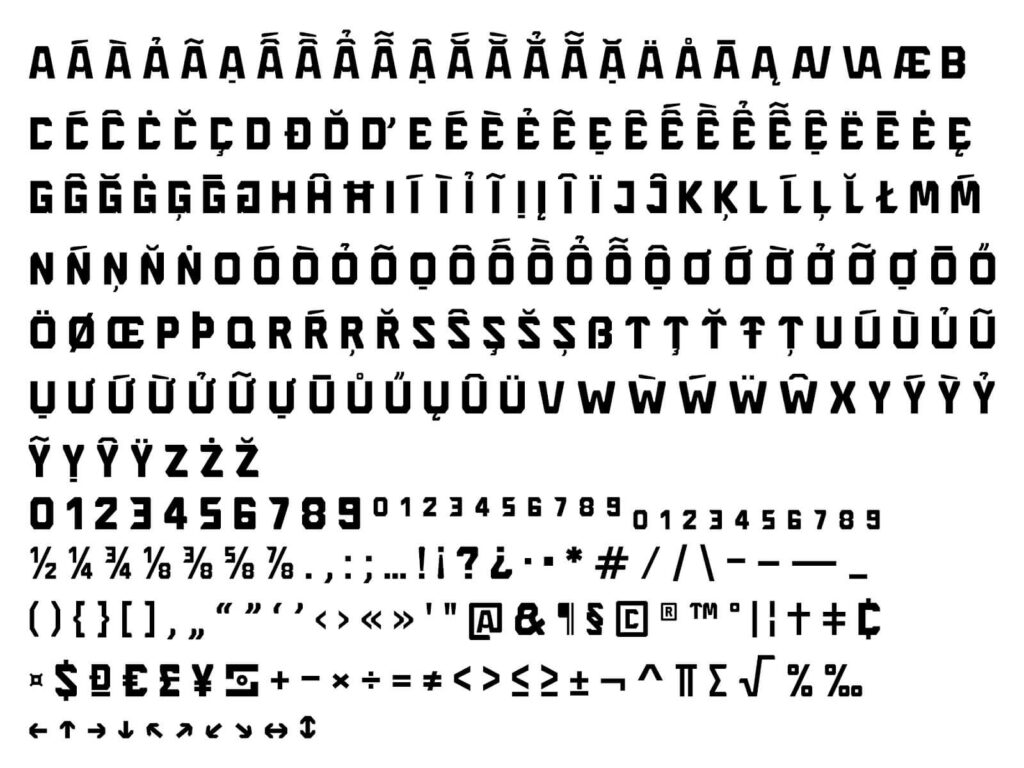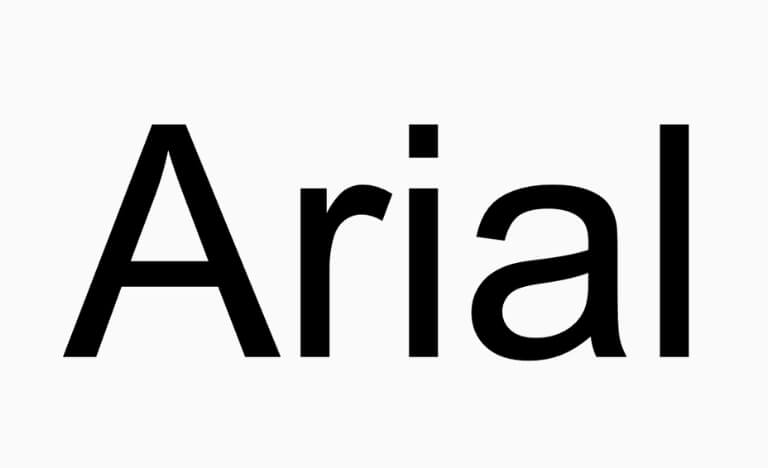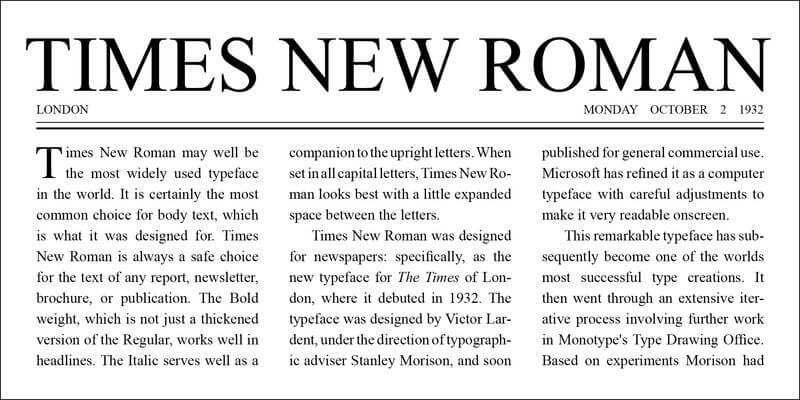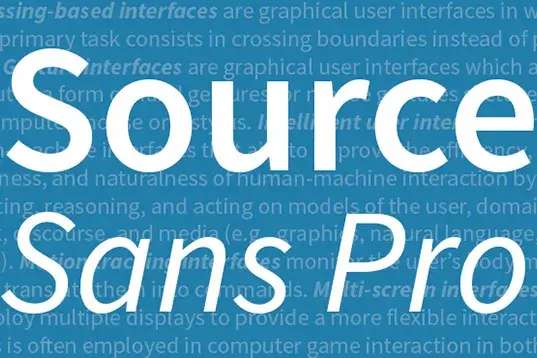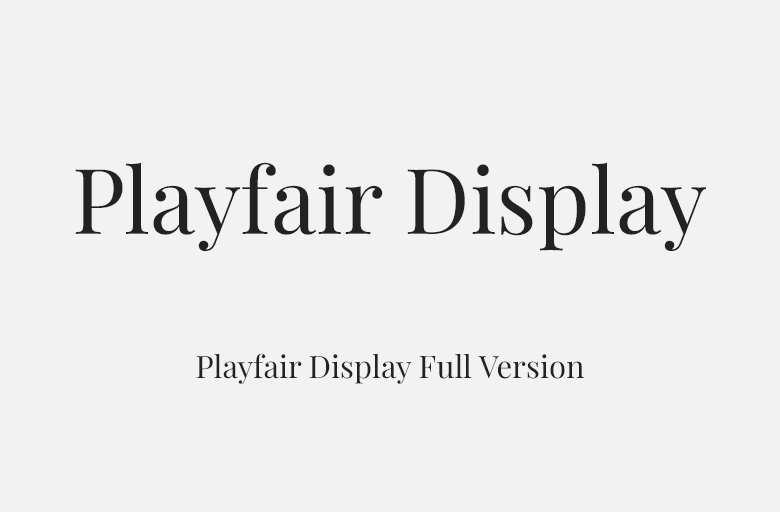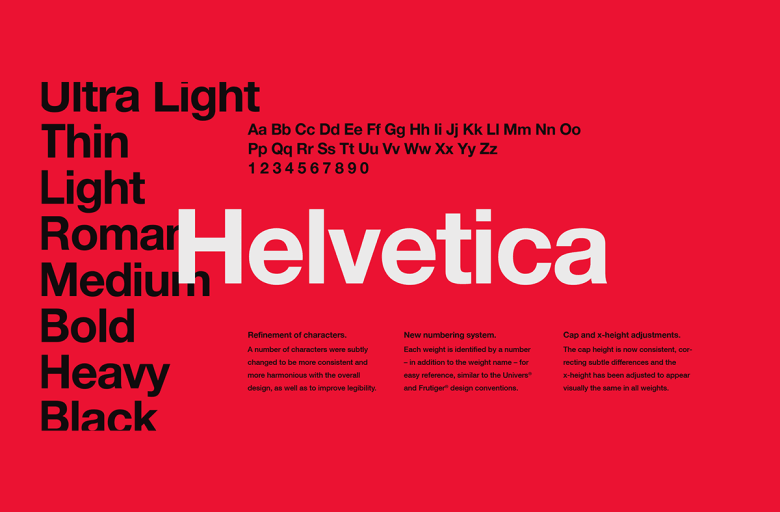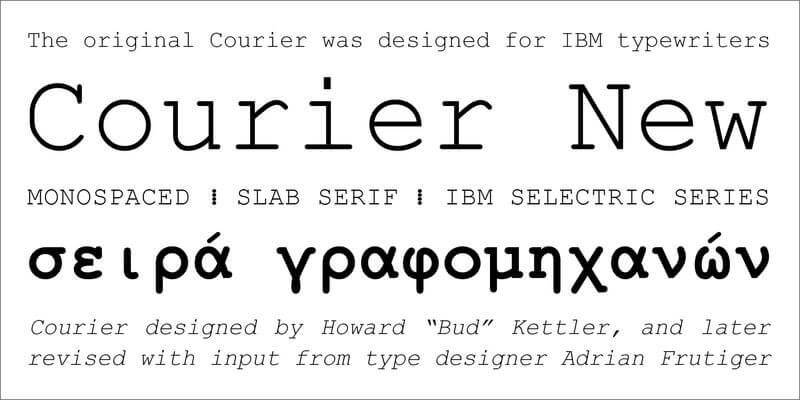
Việc lựa chọn kiểu chữ phù hợp đóng vai trò quan trọng trong việc định hình phong cách và truyền tải thông điệp của website. Để giúp bạn khám phá thế giới typography đa dạng, bài viết này sẽ giới thiệu các nhóm font chữ phổ biến, từ nét cổ điển của Serif đến sự hiện đại của Sans Serif, cùng với những lựa chọn độc đáo khác. Đặc biệt, chúng tôi sẽ mang đến một bộ sưu tập hơn 30 font chữ tiếng Việt miễn phí, được tuyển chọn kỹ lưỡng để nâng tầm thẩm mỹ và trải nghiệm người dùng trên trang web của bạn, mang đến sự chuyên nghiệp và thu hút mà bạn có thể tìm thấy tại hieuseo
Phân loại các kiểu chữ thông dụng trong thiết kế web
Trong lĩnh vực thiết kế web, việc am hiểu sâu sắc về các loại font chữ khác nhau là yếu tố then chốt để xây dựng một hệ thống typography hiệu quả, vừa đảm bảo tính thẩm mỹ, vừa tối ưu trải nghiệm người dùng. Dưới đây là bốn nhóm font chữ chính, mỗi loại mang đặc trưng và ứng dụng riêng biệt:
- Font Sans Serif
- Font Script (Chữ viết tay)
- Font Display
- Font Serif
Kiểu chữ Serif: Nét cổ điển và uy tín
Font Serif là nhóm font chữ đặc trưng bởi sự hiện diện của các đường nét nhỏ, thường được gọi là “chân chữ” hoặc “gạch ngang”, ở cuối mỗi nét chính của ký tự. Đây là một trong những kiểu chữ lâu đời nhất, gắn liền với lịch sử in ấn và các ấn phẩm truyền thống.
Đặc điểm: Có các chi tiết trang trí nhỏ (serif) tại các điểm kết thúc của nét chữ, tạo cảm giác cổ điển và trang trọng.
Công dụng phổ biến:
- Thường được sử dụng rộng rãi trong in ấn, điển hình là sách, báo, tạp chí, nơi cần duy trì sự trang trọng và dễ đọc cho văn bản dài.
- Lý tưởng cho các tài liệu chính thức, học thuật, hoặc các ấn phẩm mang tính truyền thống, lịch sử.
- Góp phần xây dựng cảm giác uy tín, tin cậy và sự ổn định cho các website tin tức, blog chuyên sâu, hoặc các tổ chức có bề dày lịch sử.
Ưu điểm: Mang lại vẻ đẹp cổ điển, trang trọng và có tính thẩm mỹ cao. Các chân chữ giúp mắt dễ dàng theo dõi dòng chữ, đặc biệt hiệu quả với các đoạn văn bản dài trên giấy.
Nhược điểm: Trên màn hình kỹ thuật số, đặc biệt ở kích thước nhỏ hoặc độ phân giải thấp, các chân chữ có thể gây khó đọc hoặc làm mất đi sự rõ ràng của ký tự.
Ví dụ tiêu biểu: Times New Roman, Georgia, Garamond.
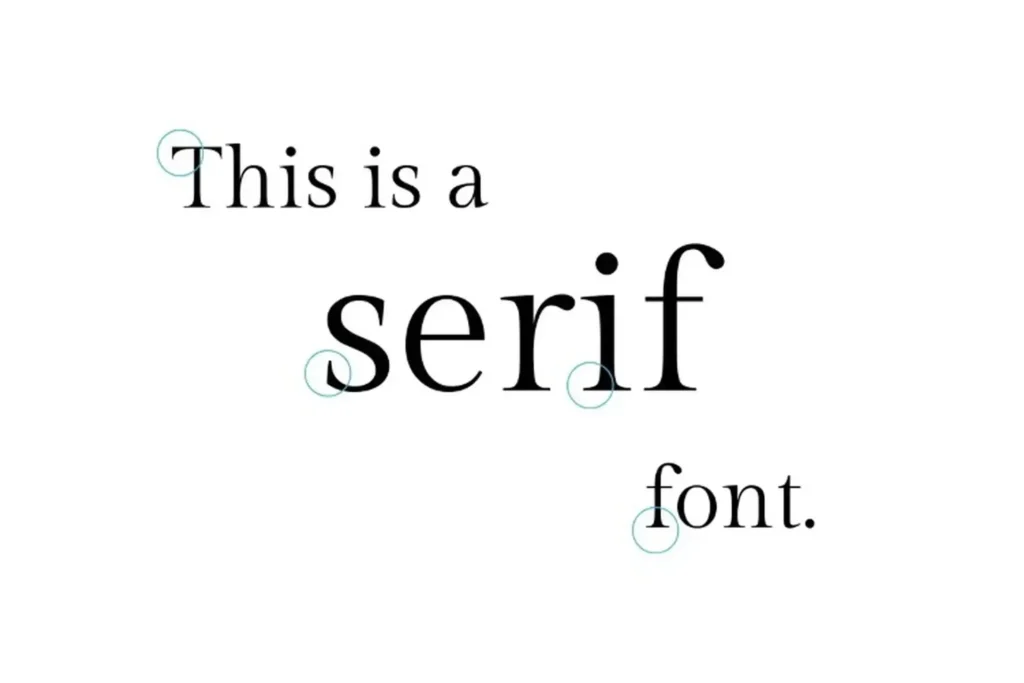
Sans Serif: Sự hiện đại và rõ ràng
Font Sans Serif là nhóm font chữ không có các nét nhỏ (serif) ở cuối các nét chính, mang đến một thiết kế sạch sẽ, hiện đại và tối giản. Sự vắng mặt của chân chữ giúp font Sans Serif trở thành lựa chọn ưu việt trong các thiết kế đương đại và giao diện người dùng kỹ thuật số.
Đặc điểm: Không có các nét nhỏ ở cuối mỗi nét chữ, tạo cảm giác gọn gàng, trực quan và hiện đại.
Công dụng phổ biến:
- Là lựa chọn hàng đầu cho nội dung số, từ màn hình máy tính để bàn đến các thiết bị di động, nhờ khả năng hiển thị rõ nét.
- Thích hợp cho các website có phong cách hiện đại, ứng dụng di động, giao diện người dùng (UI/UX) và các dự án công nghệ.
- Đặc biệt dễ đọc trên màn hình ở nhiều kích thước khác nhau, kể cả khi font chữ được thu nhỏ.
Ưu điểm: Khả năng đọc vượt trội trên màn hình kỹ thuật số, mang lại cảm giác hiện đại, sạch sẽ và linh hoạt.
Nhược điểm: Đôi khi có thể thiếu đi sự cá tính hoặc nét độc đáo nếu không được chọn lựa và kết hợp cẩn thận.
Ví dụ tiêu biểu: Arial, Helvetica, Verdana, Roboto.
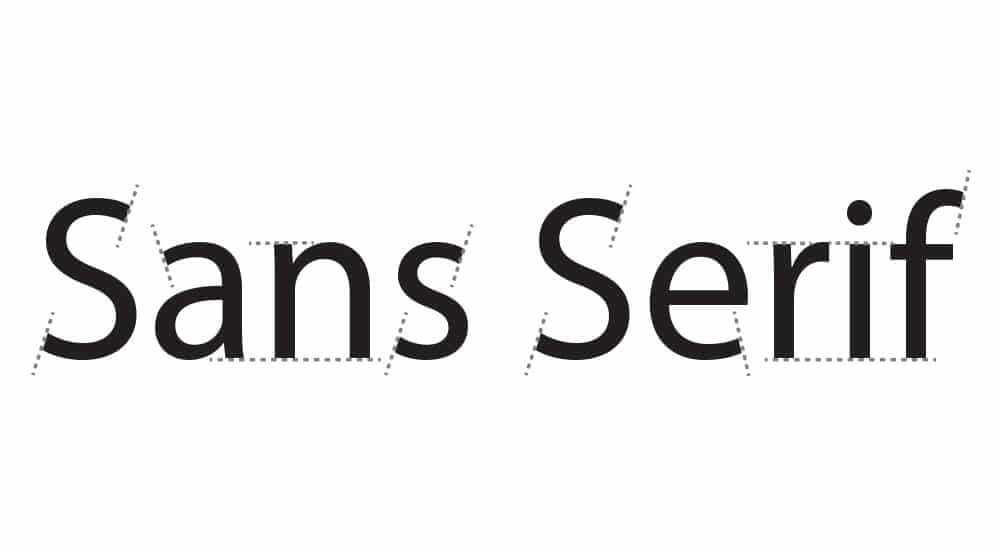
Kiểu chữ viết tay (Script): Sự mềm mại và nghệ thuật
Font Script được thiết kế để mô phỏng chữ viết tay, thư pháp hoặc các kiểu chữ được vẽ bằng tay, mang đến một phong cách cá nhân, mềm mại và giàu tính nghệ thuật. Tùy thuộc vào thiết kế cụ thể, font script có thể tạo nên sự gần gũi, thân thiện, thanh lịch hoặc thậm chí là sang trọng.
Đặc điểm: Mô phỏng chữ viết tay, thường có các nét nối liền mạch, uyển chuyển, hoặc các đường cong mềm mại.
Công dụng phổ biến:
- Thường được dùng trong các thiết kế mang tính cá nhân hóa như thiệp mời, lời chúc, hoặc các ấn phẩm kỷ niệm.
- Tạo điểm nhấn đặc biệt trong thiết kế, thu hút sự chú ý vào một phần nội dung cụ thể.
- Phù hợp cho các website về thời trang, nghệ thuật, ẩm thực, blog cá nhân hoặc các thương hiệu muốn thể hiện sự sáng tạo và độc đáo.
Ưu điểm: Độc đáo, cá tính, mang lại cảm giác ấm áp, lãng mạn hoặc sang trọng.
Nhược điểm: Khả năng đọc thường kém hơn so với Serif và Sans Serif, đặc biệt ở kích thước nhỏ hoặc khi được sử dụng cho các đoạn văn bản dài. Nên dùng hạn chế cho tiêu đề hoặc các yếu tố trang trí.
Ví dụ tiêu biểu: Pacifico, Dancing Script, Brush Script MT.
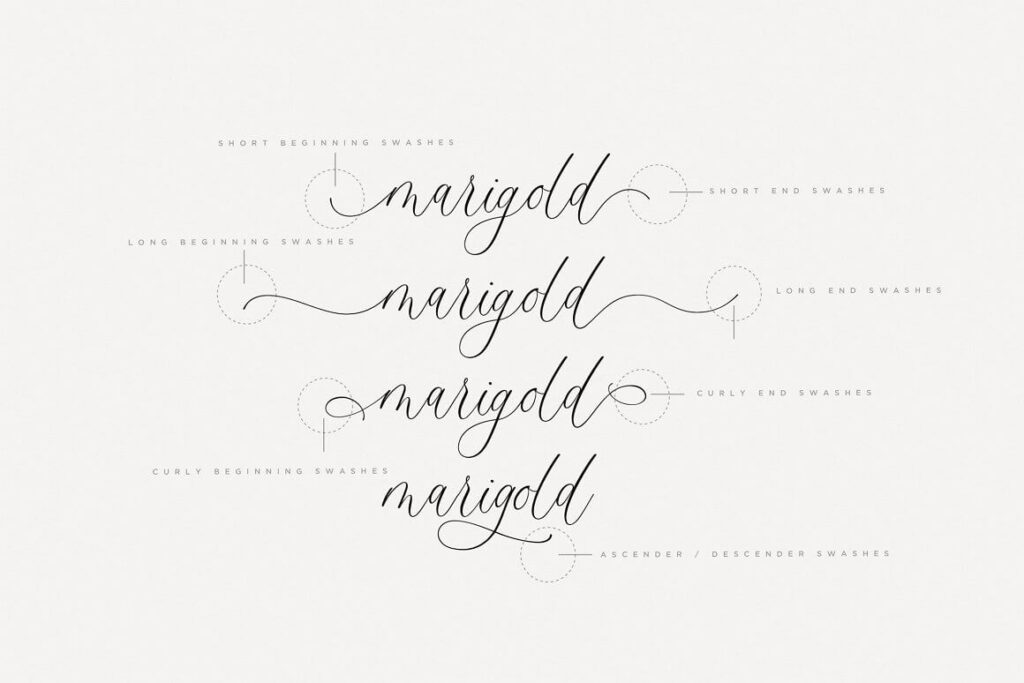
Kiểu chữ Display: Dành cho tiêu đề và logo nổi bật
Font Display là nhóm font chữ được thiết kế chuyên biệt để sử dụng ở kích thước lớn, chủ yếu dành cho các tiêu đề, logo, biển hiệu hoặc các yếu tố đồ họa cần tạo ấn tượng mạnh mẽ. Các font Display thường có thiết kế độc đáo, phá cách và được tối ưu để thu hút sự chú ý ngay lập tức.
Đặc điểm: Thiết kế độc đáo, thường rất ấn tượng, có tính trang trí cao và được tối ưu để hiển thị ở kích thước lớn.
Công dụng phổ biến:
- Lý tưởng cho các tiêu đề chính, khẩu hiệu (slogan) hoặc các thông điệp cần sự nổi bật.
- Tạo hệ thống phân cấp rõ ràng: Sử dụng các kích thước, trọng lượng (bold/regular) và màu sắc khác nhau để phân biệt tiêu đề chính, phụ đề và nội dung thân bài.
- Đảm bảo sự nhất quán: Luôn sử dụng cùng một font cho các yếu tố tương tự trên toàn bộ website (ví dụ: tất cả các tiêu đề H1 đều dùng một font, tất cả các đoạn văn bản đều dùng một font khác).